Trong lĩnh vực thiết kế đồ họa, việc lựa chọn font chữ phù hợp có thể tạo ra sự khác biệt lớn trong việc truyền tải thông điệp và tạo ấn tượng cho người xem. Một trong những ứng dụng quan trọng của font chữ chính là trong việc thiết kế giấy khen. Những mẫu giấy khen không chỉ cần có hình thức đẹp mắt mà còn phải thể hiện sự chuyên nghiệp và sang trọng. Trong bài viết này, chúng tôi sẽ giới thiệu đến bạn 15+ font chữ giấy khen, giúp bạn tạo ra những mẫu giấy khen ấn tượng và chuyên nghiệp nhất.
Font chữ là yếu tố thiết kế không thể thiếu trong bất kỳ dự án nào. Đặc biệt đối với giấy khen, nó không chỉ đóng vai trò là phương tiện truyền tải thông tin mà còn ảnh hưởng đến cảm nhận của người nhận. Khi lựa chọn font chữ cho giấy khen, bạn cần lưu ý một số tiêu chí sau:
Tính dễ đọc: Font chữ cần phải rõ ràng và dễ đọc từ khoảng cách xa.
Phong cách: Lựa chọn font chữ phù hợp với chủ đề và phong cách của sự kiện.
Sự hài hòa: Font chữ phải hòa hợp với các yếu tố thiết kế khác như màu sắc, hình ảnh.
Định dạng: Một số font chữ có thể đẹp nhưng lại khó sử dụng trong các định dạng in ấn.
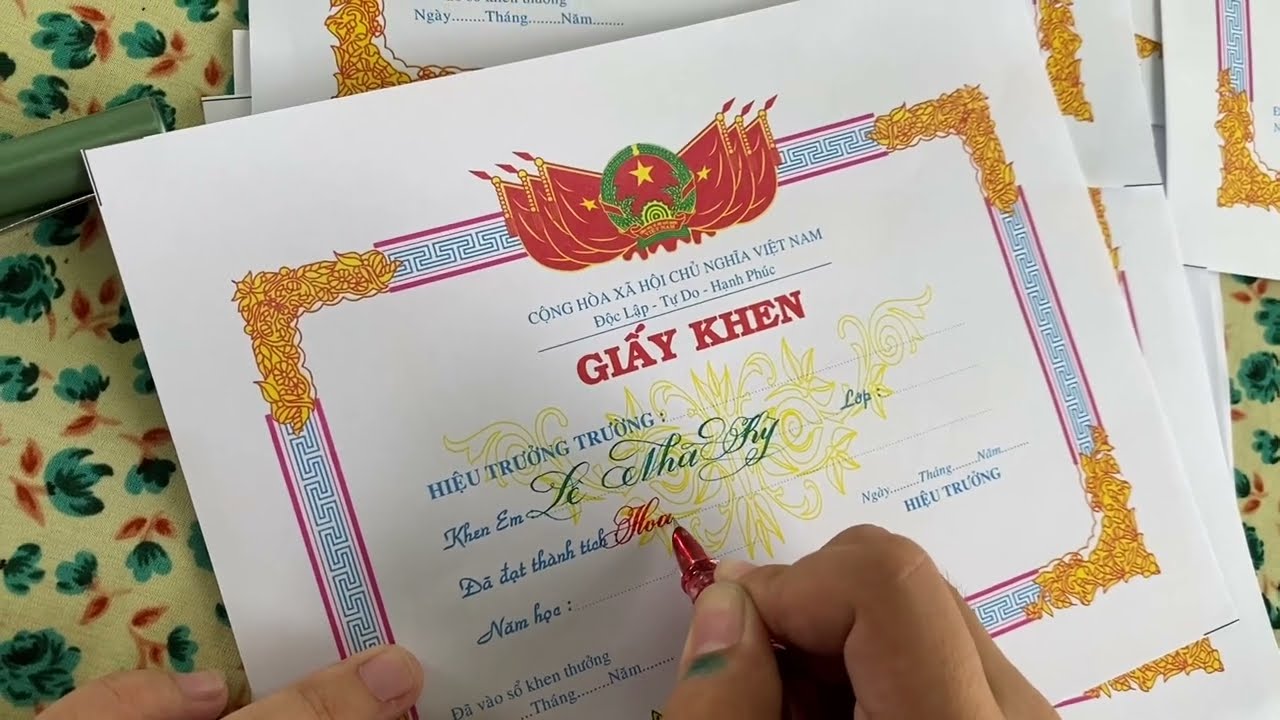
Dưới đây là danh sách 15+ font chữ giấy khen bạn có thể tải xuống và sử dụng cho các dự án thiết kế của mình. Các font chữ này đều mang tính chuyên nghiệp và sang trọng, phù hợp cho việc thiết kế giấy khen.
Font chữ có chân (serif fonts) thường được ưa chuộng trong thiết kế giấy khen kiểu truyền thống và nhà nước vì tính lịch sự, trang trọng và dễ đọc. Những font chữ này không chỉ tạo ra cảm giác nghiêm túc mà còn thể hiện sự tôn trọng đối với người nhận giải thưởng. Dưới đây là một số lý do và ví dụ về các font chữ có chân phù hợp cho giấy khen:
Tính trang trọng và lịch sử: Font chữ có chân thường mang lại cảm giác truyền thống và trang trọng. Điều này rất quan trọng trong các tài liệu như giấy khen, nơi mà việc thể hiện sự tôn trọng đối với người nhận là rất cần thiết.
Dễ đọc: Với các đặc điểm chân chữ rõ ràng, font chữ có chân giúp nâng cao khả năng đọc hiểu. Khi người nhận nhìn vào giấy khen, họ sẽ dễ dàng đọc tên, danh hiệu và lý do nhận giải mà không bị nhầm lẫn.
Thích hợp cho các dịp chính thức: Trong các sự kiện, lễ trao giải, hay chứng nhận từ các cơ quan nhà nước, font chữ có chân thường được coi là tiêu chuẩn, phù hợp với bối cảnh chính thức.
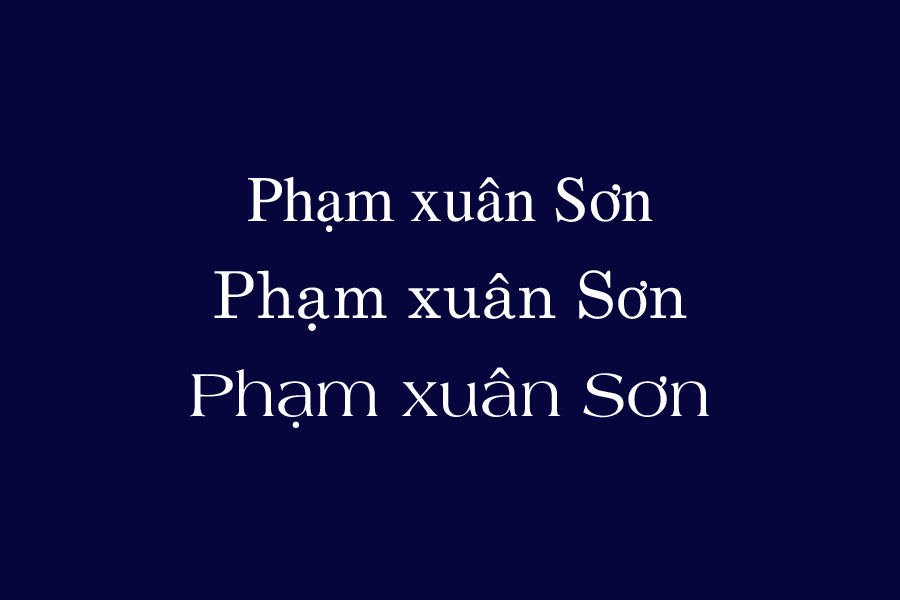
Trong thiết kế giấy khen, việc chọn font chữ cho phần ghi họ tên là vô cùng quan trọng, vì nó thể hiện sự cá nhân hóa và tôn trọng đối với người nhận. Dưới đây là ba font chữ viết tay trong bộ UVN, mang đến vẻ đẹp độc đáo và gần gũi, giúp làm nổi bật tên người nhận một cách tinh tế.
Font chữ nghiêng UVN Việt hóa mang đến một phong cách viết tay mềm mại và tự nhiên, phù hợp cho các thiết kế cần thể hiện sự thân thiện và gần gũi. Đặc biệt, sự nhấn nhá nhẹ nhàng trong các chữ cái giúp tăng tính thẩm mỹ, khiến giấy khen trở nên đặc biệt hơn. Đây là một lựa chọn tuyệt vời cho những ai muốn tạo ra một mẫu giấy khen độc đáo và thu hút.
Font chữ thanh lịch hiện đại - TH Calgria
Font chữ Calgria mang đến sự thanh lịch và hiện đại, rất phù hợp cho việc thiết kế giấy khen, bằng khen và các sự kiện trang trọng. Với đường nét mềm mại, font chữ này giúp tạo ra không gian trang trọng mà vẫn giữ được sự tinh tế.
Lựa chọn font chữ giấy khen là một yếu tố quan trọng trong thiết kế, giúp tạo ra sự chuyên nghiệp và sang trọng cho sản phẩm cuối cùng. Với danh sách 15+ font chữ giấy khen được S99.vn giới thiệu trong bài viết này, hy vọng bạn sẽ tìm được những font chữ phù hợp nhất cho dự án của mình.
Đừng quên rằng việc sử dụng font chữ đúng cách không chỉ tạo ra một mẫu giấy khen đẹp mà còn mang đến ấn tượng tốt cho người nhận. Hãy lựa chọn và tải xuống những font chữ giấy khen này để tạo nên những thiết kế ấn tượng nhất!|